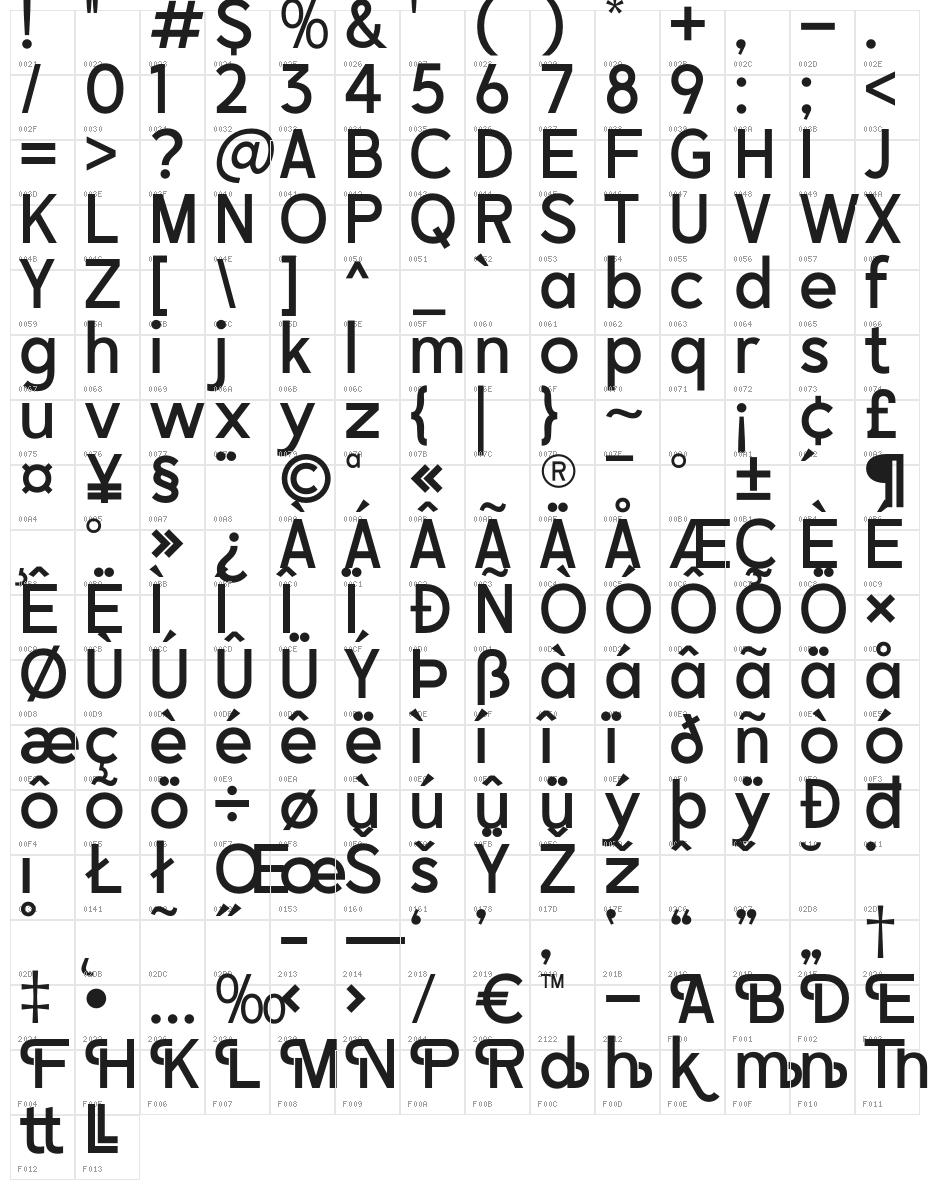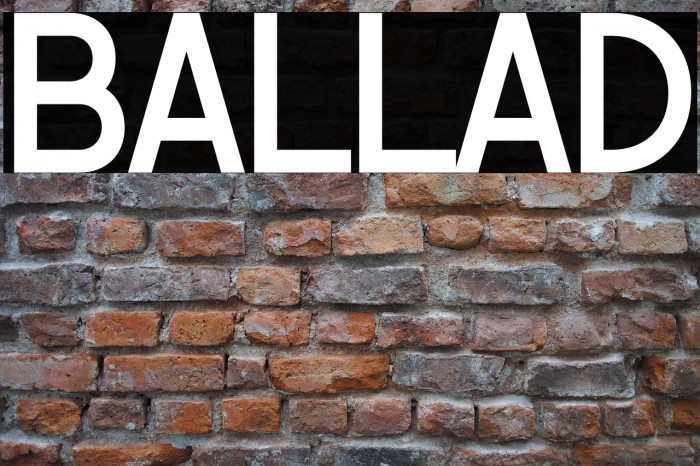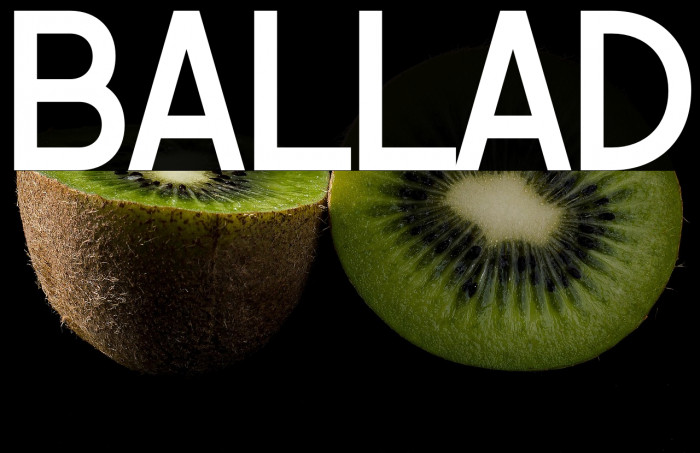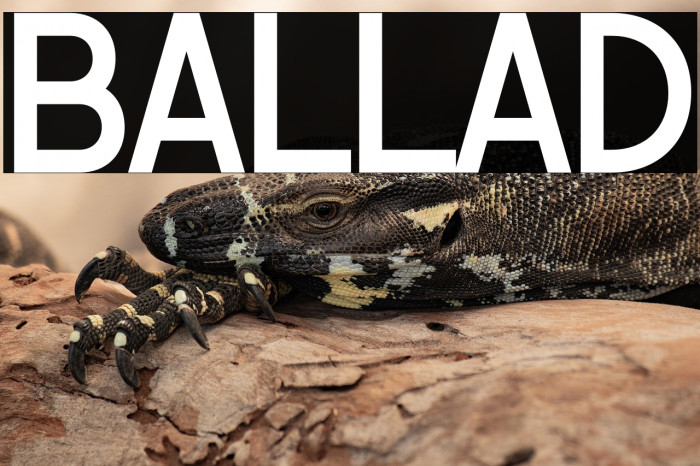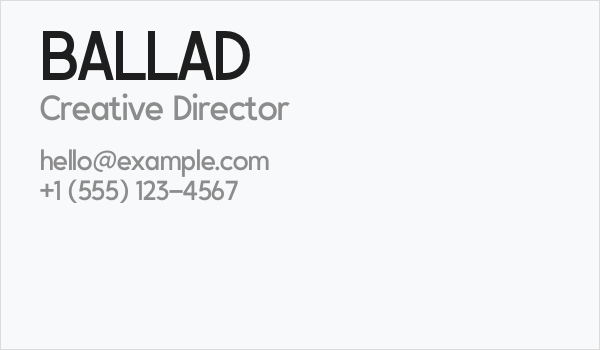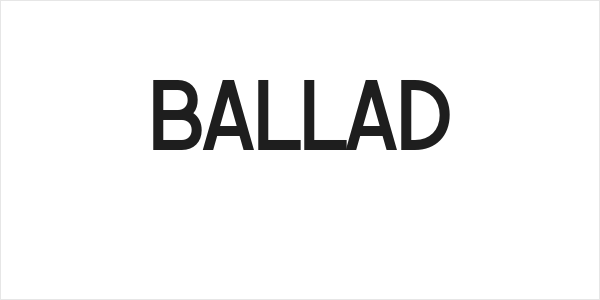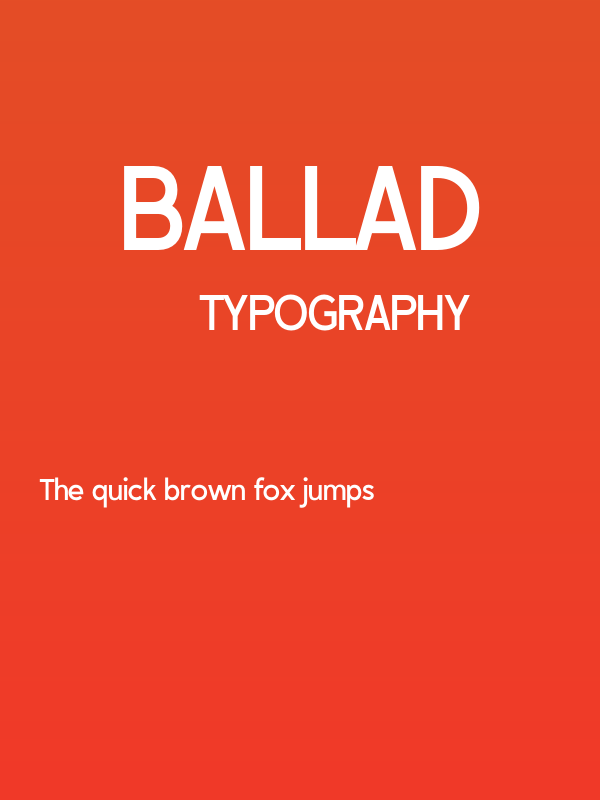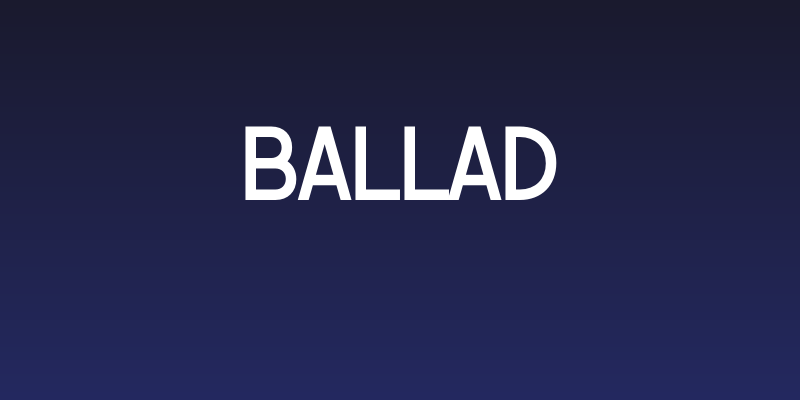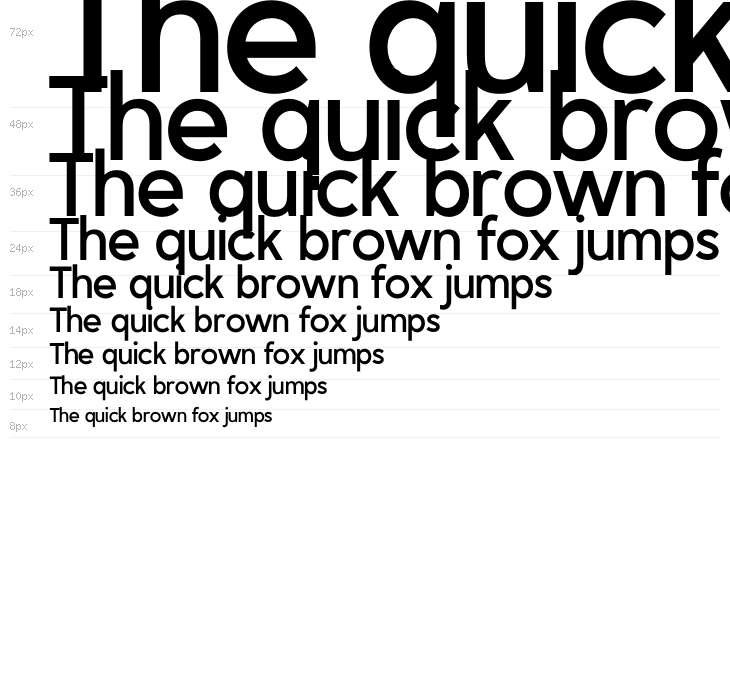
BALLAD Font
| Nome | BALLAD |
| Progetti proposti | Ideal for branding, advertising, web design, and editorial layouts due to its clarity and modern appeal. |